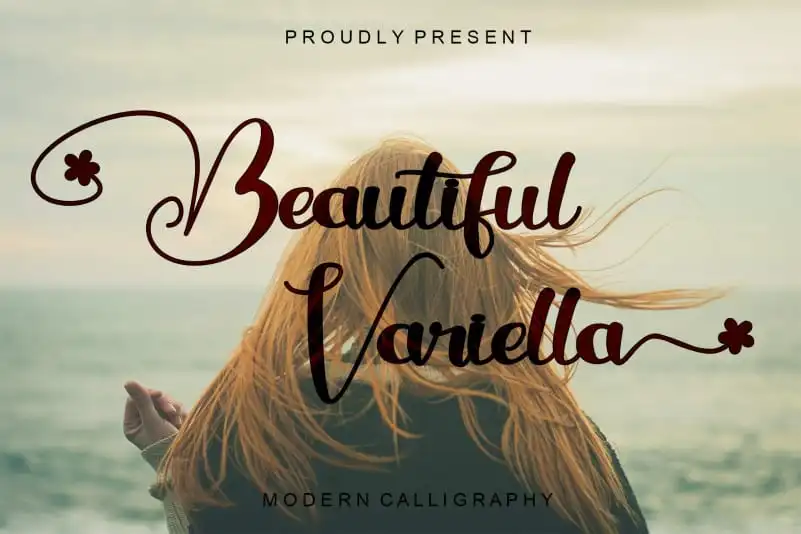
A Beautiful variella Calligraphy Font é uma elegante seleção para aqueles que desejam dar vida a letras chamativas e formais com destaque. Desenvolvida pelo talentoso designer Ahmad Afandi, esta fonte Script traz um ar de sofisticação perfeita para aplicações em estilos de headlines inovadores, bem como para formas formais utilizadas em cartões de convite, logotipos, revistas, livros e até mesmo nas embalagens de produtos. Seja para dar vida a uma caixa de cosméticos ou um envelope de notícias, a Beautiful variella Calligraphy Font oferece as ferramentas ideais para criar mensagens que chamem a atenção. Uma fonte perfeita não só para publicidade e comunicação visual formal, mas também ideal para criações em estilos criativos e artísticos.